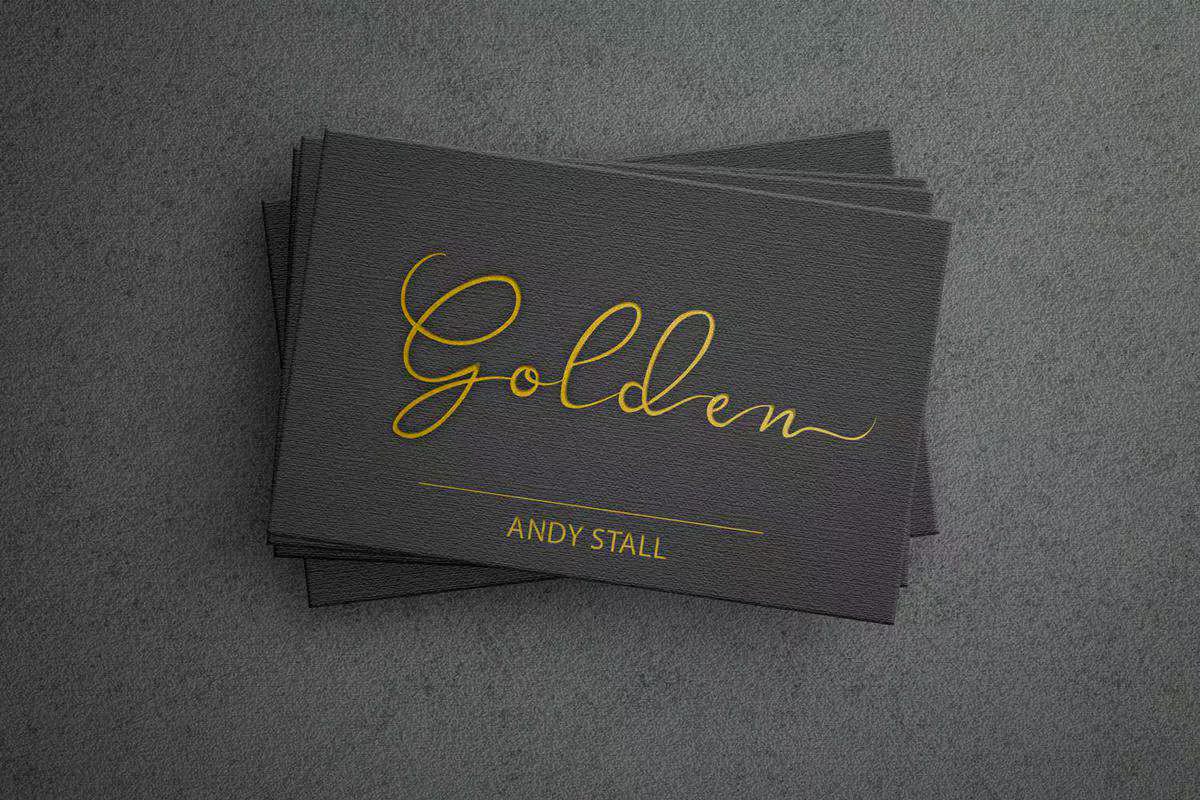
Wollastonisastylish and Delicate ScriptFont。对于您要添加的任何设计,它都是干净、薄、平滑的,并且不会损坏。Wollastonispuded表示您可以访问所有图示符和Swashease!Wollastonisastylish and Delicate ScriptFont。对于您要添加的任何设计,它都是干净、薄、平滑的,并且不会损坏。Wollastonispuded表示您可以访问所有图示符和Swashease!